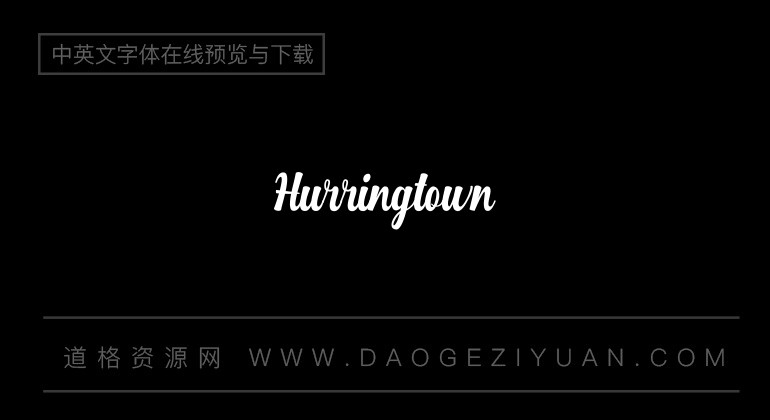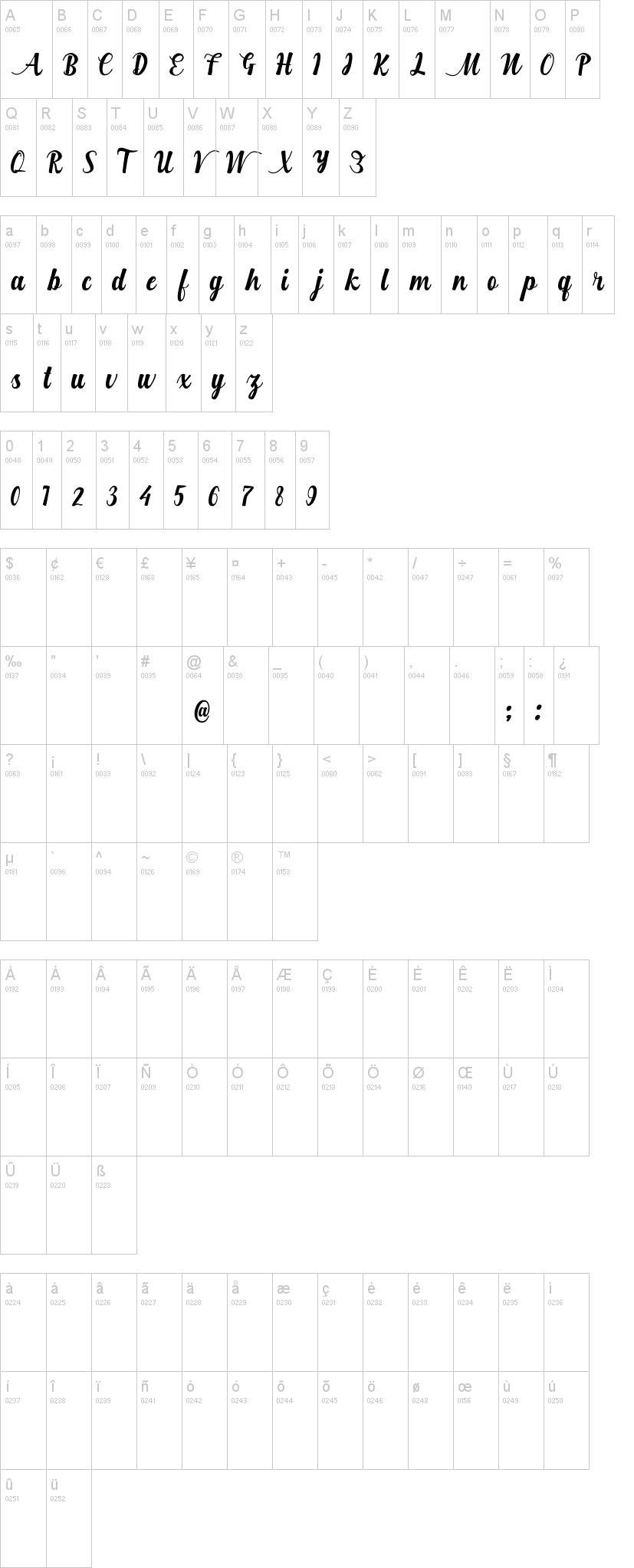
? Hurringtown 字体是一款新潮的抽象字体,由英国设计师 Rian Hughes 设计。这款字体灵感来自于 20 世纪 30 年代的抽象艺术,具有流畅的线条和抽象的形状,以及强烈的视觉冲击感。它具有极高的视觉冲击力,可以用来设计海报、标志和各种其他印刷品,以及网页设计等。内容介绍
Hurringtown是一款非常不错的手写艺术字体,具有很好的视觉感,适合于文化类的宣传设计、商业类品牌的广告和产品包装设计以及个性化文字排版等较多场景。